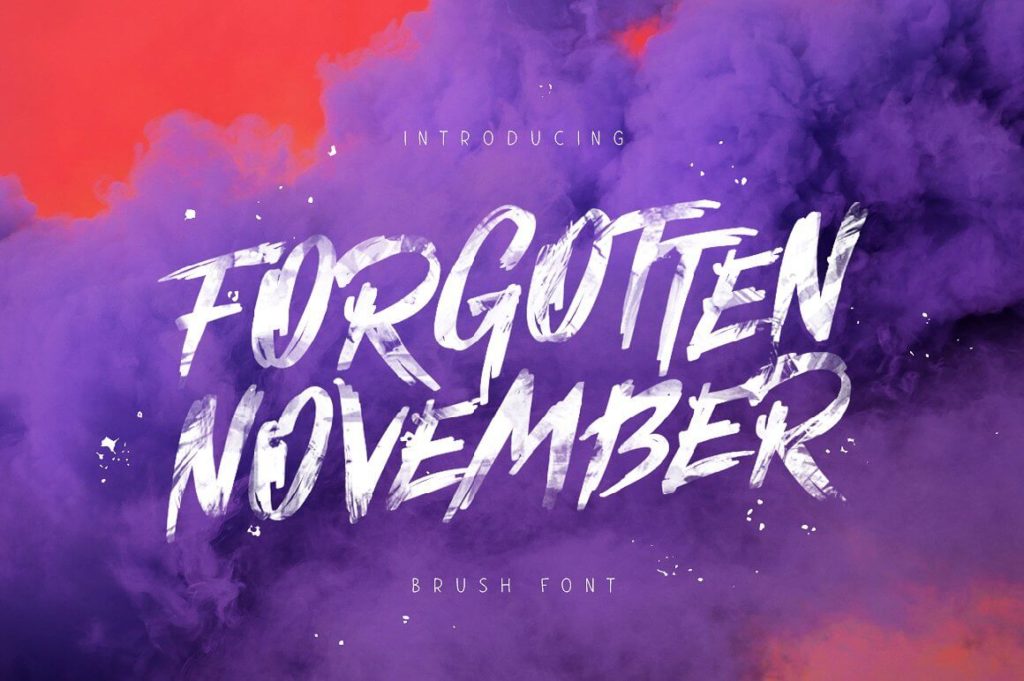
это выразительный рукописный шрифт от студии ChekArt, выпущенный в 2018 году. Он имитирует естественное письмо ручкой с легким винтажным налетом, создавая атмосферу уюта и ностальгии. Шрифт полностью адаптирован для набора кириллических текстов, что избавляет дизайнеров от проблем с заменой символов при верстке. Благодаря характерному рисунку букв, наличию лигатур и декоративных элементов, он отлично подходит для создания атмосферных заголовков, приглашений и фирменного стиля в стиле рустик или бохо. Скачать бесплатно кириллическую версию можно на нашем сайте